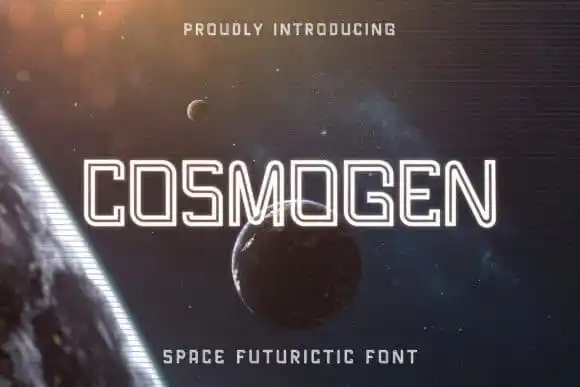
Cosmogen Display Font – Download Grátis
A fonte ‘Cosmogen Display Font’ é uma criação luminosa que representa a letra do alfabeto neon. Desenvolvida pela Typefactory e compartilhada para quem busca um estilo vibrante e futurista, esta fonte perfeita para temáticas tecnológicas, científicas-ficcionais, digitais, além de temas espaciais e galáxias. Ideal tanto para projetos visuais que remetem à cultura do cinema – como trailers ou capas de livros -, quanto para elementos gráficos de jogos e filmes, ‘Cosmogen Display Font’ também se destaca em títulos, headlines e até mesmo em campanhas publicitárias. Suas linhas fortes e iluminadas criam um contraste atraente que faz da fonte uma escolha inteligente para qualquer projeto que precise de uma identidade visual chamativa e moderna.